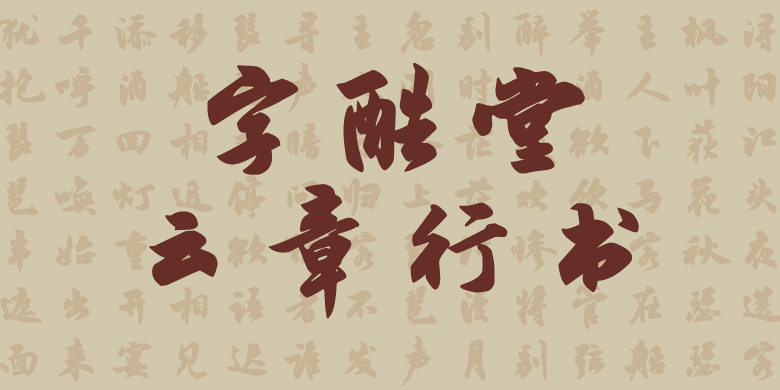
字酷堂云章行书
行楷、常规书写·毛笔
字酷堂云章行书,字体风格源于米芾,同时也融合了苏轼行书的特点。字体笔划线条刚柔并济,圆润饱满,转折灵动洒脱,结字严谨而不失变化,兼具古典韵律与现代审美张力。米芾,字元章,与蔡襄、苏轼、黄庭坚合称“宋四家”。米芾早年遍临诸家,晚年融会贯通形成独特“米体”。他既继承二王笔意,又突破传统正局,以偏侧取势开创书法新境,这种“师古而不泥古”的创新精神,使其成为书法史上承前启后的重要人物。